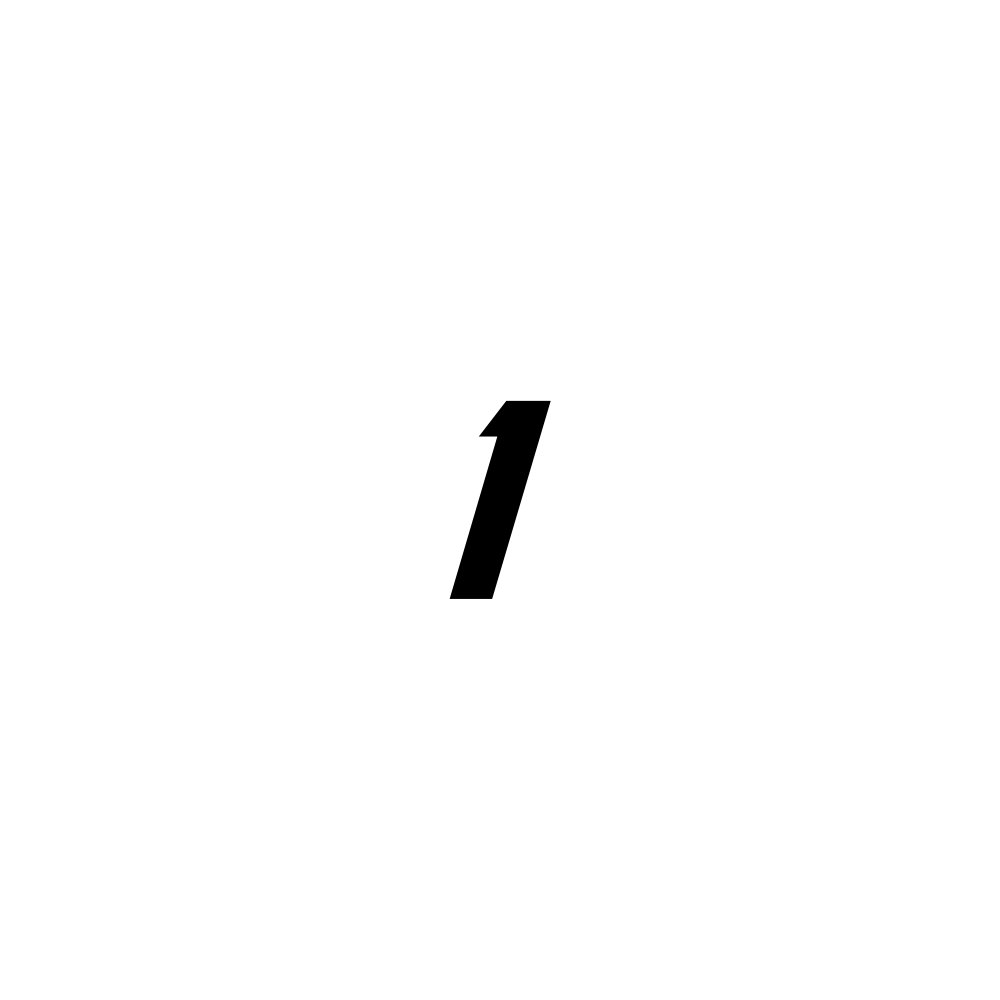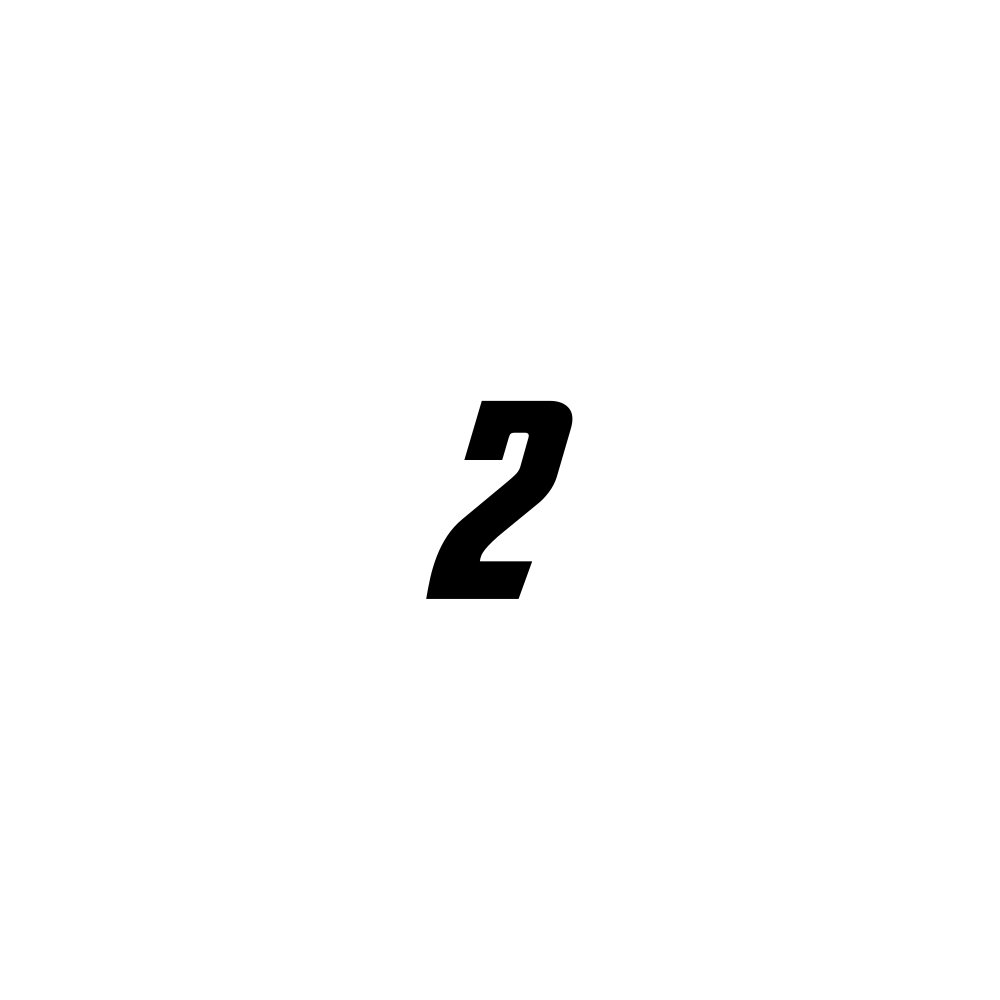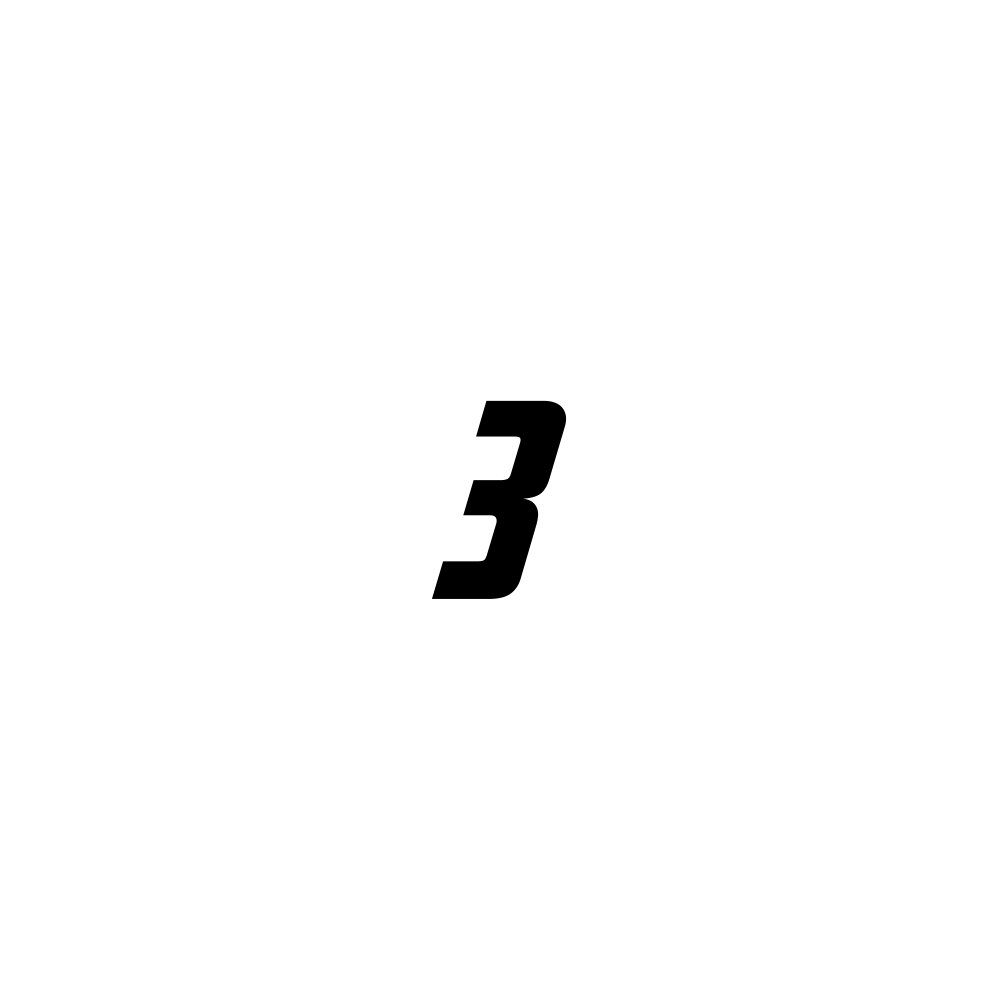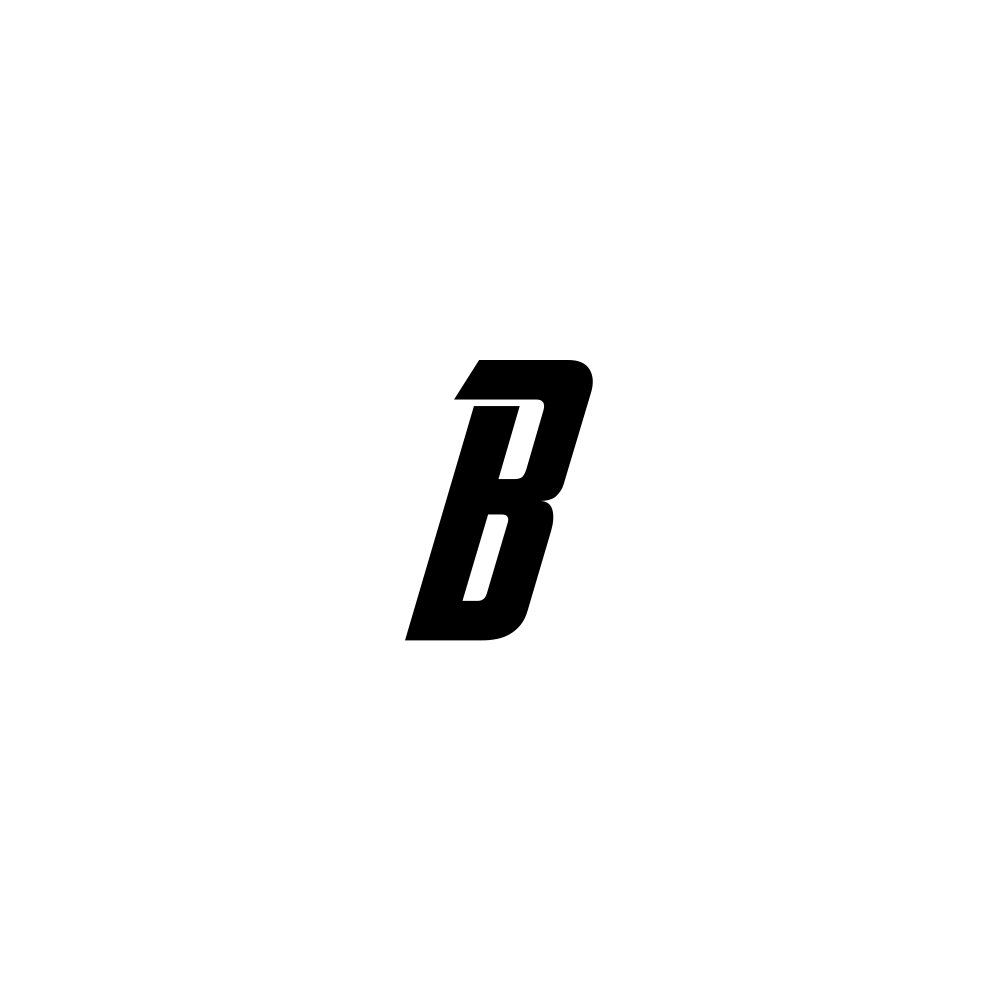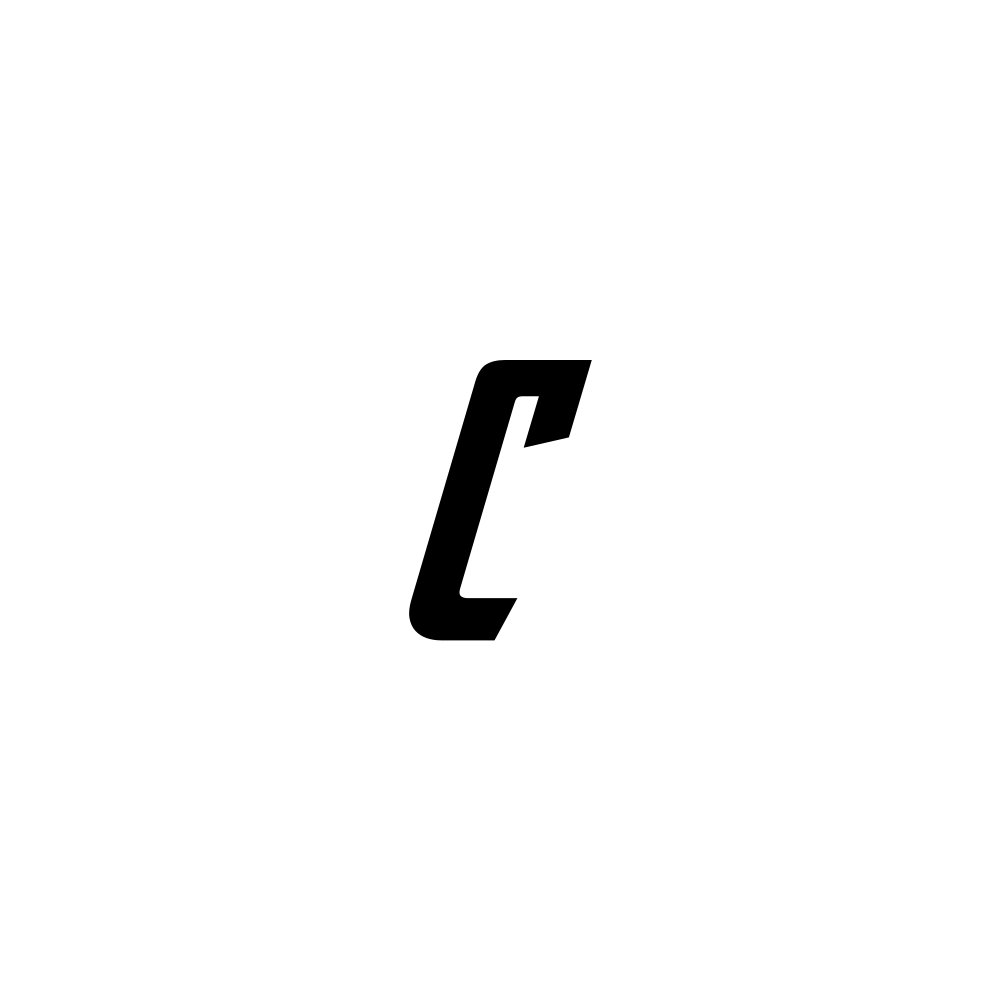
Hero Strike Monogramm Schriftart – Kräftiges Action-Alphabet mit Grossbuchstaben, Kleinbuchstaben, Zahlen und Satzzeichen | Cricut-kompatibel
• Die Hero Strike Monogramm Schriftart ist eine kräftige, dynamische Display-Schrift, inspiriert von klassischen Comic- und Superhelden-Schriftstilen. Die Buchstaben besitzen markante, leicht geneigte Formen mit scharfen Kanten und klaren Linien, wodurch der Text eine energiegeladene und kraftvolle Wirkung erhält. Trotz des dramatischen Stils bleiben die Zeichen gut lesbar und strukturiert.
• Die Schrift enthält Grossbuchstaben, Kleinbuchstaben, Zahlen sowie Satzzeichen, wodurch sie für viele kreative Projekte verwendet werden kann. Die starken Buchstabenformen eignen sich besonders gut für Monogramme, Namen, personalisierte Designs und auffällige Überschriften, die eine starke visuelle Wirkung erzeugen sollen.
• Die leicht kompakte Struktur und die sauberen Kanten sorgen dafür, dass die Buchstaben klar dargestellt und sauber geschnitten werden können. Dadurch eignet sich die Schrift ideal für verschiedene Bastel- und Designanwendungen. Ob für Monogramm-Schriftzüge, individuelle Namen oder dekorative Titel, diese Schrift verleiht Projekten einen selbstbewussten und kraftvollen typografischen Stil.